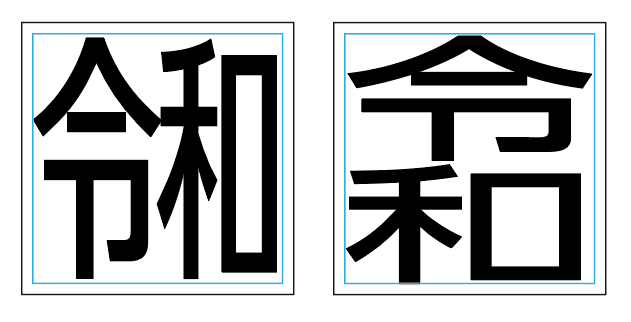
【令和合字とは】
令和合字とは、「令和」の2文字が全角1文字分のスペースに入るようにデザインされた文字のことです。
縦組みの合字は、AP版書体のうち、ProN, Pr5N, Pr6N書体に収録しています。
StdN書体では横組みの合字のみご利用いただけます。
【対応状況について】
令和合字の対応状況
2019年10月24日以降にリリースした新書体は令和合字に対応しています。
既存書体の対応について
既存書体については、今後AP版書体としてリリースされるフォントで対応いたします。
※AP版書体とは、書体名が「A P-OTF」から始まる書体です。
【よくあるご質問】
令和合字を使用したデータを、令和合字に対応していない書体で開くとどうなりますか?
令和合字が解除される、令和合字に対して適用したはずの書体が適用されない、などの現象が確認されていますが、お客様環境によっておこる影響は様々です。
令和合字を使用したデータは、令和合字に対応した同書体で開いていただくことを推奨します。
今後の対応予定について
StdN, ProN, Pr5N, Pr6NでリリースするAP版書体については令和合字に対応します。